8 แบบอักษรที่ดีที่สุดสำหรับเว็บไซต์ของคุณ
เผยแพร่แล้ว: 2023-02-12แบบอักษรที่คุณใช้บนเว็บไซต์ของคุณบ่งบอกความเป็นแบรนด์ของคุณได้มากมาย แบบอักษรบนเว็บแต่ละแบบมีลักษณะเฉพาะของตัวเองและช่วยในการถ่ายทอดข้อความของธุรกิจของคุณ อย่างไรก็ตาม ด้วยตัวเลือกที่หลากหลาย อาจเป็นเรื่องยากที่จะทราบว่าตัวเลือกใดเหมาะสมกับไซต์ของคุณ
โชคดีที่มีหลายปัจจัยที่สามารถช่วยคุณเลือกแบบอักษรสำหรับแบรนด์ของคุณได้ เมื่อดูตัวอย่างและการใช้งาน คุณจะสามารถเลือกแบบอักษรที่สื่อสารเรื่องราวและบุคลิกของคุณได้
ในโพสต์นี้ เราจะดูที่ประเภทต่างๆ ของฟอนต์และลักษณะเฉพาะของฟอนต์ จากนั้นเราจะตรวจสอบแบบอักษรบนเว็บที่ดีที่สุดสำหรับเว็บไซต์ธุรกิจและบล็อก สุดท้าย เราจะแบ่งปันเคล็ดลับบางอย่างเพื่อช่วยคุณเลือกสไตล์สำหรับไซต์ของคุณ มาเริ่มกันเลย!
ความรู้เบื้องต้นเกี่ยวกับแบบอักษร
แบบอักษรเป็นคุณลักษณะที่สำคัญของเว็บไซต์ของคุณ คุณอาจรู้จัก Times New Roman ในหัวเรื่องและ Arial ในเนื้อหาของโพสต์ แต่ฟอนต์มีมากกว่าที่เห็น
จากการศึกษาเมื่อเร็วๆ นี้ ผู้บริโภค 75 เปอร์เซ็นต์จะตัดสินธุรกิจจากการออกแบบเว็บไซต์ ดังนั้น แบบอักษรที่คุณใช้จึงมีบทบาทสำคัญในวิธีที่ผู้เยี่ยมชมไซต์ของคุณรับรู้ถึงแบรนด์ของคุณ
มีแบบอักษรมากกว่า 550,000 แบบบนอินเทอร์เน็ต ส่วนใหญ่สามารถจำแนกออกได้เป็น 1 ใน 4 ประเภท ได้แก่ serif, sans serif, script และ display/decorative มาดูกันว่ากลุ่มเหล่านี้แตกต่างจากกลุ่มอื่นอย่างไร
เซริฟ
แบบอักษร Serif แบ่งตามเส้นเล็กๆ ที่ท้ายตัวอักษรแต่ละตัว มักพบในหนังสือพิมพ์และหนังสือเรียน นอกจากนี้ เว็บไซต์ข่าวหลายแห่ง เช่น The Atlantic ใช้ฟอนต์ serif:
ตัวอย่างยอดนิยม ได้แก่ Times New Roman และ Verona ตระกูลฟอนต์นี้สื่อถึงขนบธรรมเนียมและความเป็นทางการ
ซานเซอริฟ
Sans serifs เป็นแบบอักษรที่แพร่หลายมากที่สุดบนอินเทอร์เน็ต พวกเขาสะอาดและเรียบง่ายและมาโดยไม่มีเสียงระฆังหรือนกหวีด
นอกจากนี้ sans serif ยังส่งเสริมอำนาจและความไว้วางใจ อันที่จริง ฟอนต์เหล่านี้ใช้กันอย่างแพร่หลายในไซต์ของบริษัท:
สไตล์ sans serif ยอดนิยม ได้แก่ Open Sans และ Arial ฟอนต์เหล่านี้ช่วยให้คุณดูร่วมสมัยได้
สคริปต์
ตามชื่อที่แนะนำ ฟอนต์สคริปต์ (หรือฟอนต์ตัวสะกด) คล้ายกับลายมือ พวกเขามีชีวิตชีวาและสนุกสนาน ดังนั้นจึงสามารถใช้เพื่อถ่ายทอดความคิดสร้างสรรค์และความสนุกสนาน:
Lobster และ Pacifico เป็นสองตัวอย่างแบบอักษรของสคริปต์ เนื่องจากแบบอักษรเหล่านี้มีความสร้างสรรค์มากกว่า จึงมักพบในโฆษณาที่โปรโมตเทศกาลและกิจกรรมทางวัฒนธรรมอื่นๆ
แสดง
Display (เรียกอีกอย่างว่าการตกแต่ง) เป็นกลุ่มฟอนต์ที่มีศิลปะที่สุด แบบอักษรเหล่านี้มักจะคล้ายกับการประดิษฐ์ตัวอักษรและมักใช้ในหัวเรื่องหรือโลโก้:
แบบอักษรนี้เป็นตัวหนาและสร้างสรรค์ คุณสามารถค้นหาฟอนต์สำหรับตกแต่งได้จากหลากหลายไซต์ รวมถึงบล็อกทางวัฒนธรรมและร้านบูติกของช่างฝีมือ
สิ่งที่ควรทราบเมื่อเลือกแบบอักษร
มีหลายสิ่งที่ต้องพิจารณาในการเลือกแบบอักษรสำหรับเว็บไซต์ของคุณ ก่อนอื่น คุณจะต้องนึกถึงคุณค่าที่คุณต้องการสื่อสาร
ตัวอย่างเช่น หากคุณเป็นบริษัทมืออาชีพที่มีลูกค้าที่มีชื่อเสียง คุณคงไม่ต้องการเลือกแบบอักษรที่สื่อถึงความไม่เป็นทางการหรือความสนุกสนาน ในทางกลับกัน หากคุณเป็นธุรกิจขนาดเล็กที่ขายเครื่องปั้นดินเผาและงานฝีมืออื่นๆ แบบอักษรธรรมดาและจริงจังอาจไม่สะท้อนถึงคุณค่าทางศิลปะของแบรนด์ของคุณ
แบบอักษรของคุณสามารถให้ความรู้สึกบางอย่างได้ ดังนั้น สิ่งสำคัญคือต้องเลือกแบบอักษรที่สามารถช่วยให้คุณกระตุ้นอารมณ์ที่ต้องการจากผู้เยี่ยมชม เช่น ความตื่นเต้นหรือความไว้วางใจ
ความสามารถในการอ่านเป็นอีกแง่มุมหนึ่งที่ต้องพิจารณา เมื่อแบบอักษรของคุณสะอาดและเรียบง่าย จะทำให้ข้อความของคุณอ่านง่ายขึ้น แม้ว่าส่วนหัวที่ละเอียดจะเหมาะสำหรับการดึงดูดความสนใจ แต่แบบอักษรที่เรียบง่ายจะดีกว่าสำหรับเนื้อหาของโพสต์หรือเพจของคุณ
นอกจากนี้ คุณจะต้องแน่ใจว่าฟอนต์ของคุณเป็นมิตรกับผู้ใช้ การเลือกแบบอักษรที่ดีที่สุดสำหรับผู้ที่มีความบกพร่องทางการอ่านและความบกพร่องทางสายตาสามารถบ่งบอกแบรนด์ของคุณได้มากมาย แสดงให้เห็นว่าคุณเป็นธุรกิจที่ครอบคลุม นอกจากนี้ยังทำให้เว็บไซต์ของคุณเข้าถึงผู้ชมได้กว้างขึ้น
8 แบบอักษรที่ดีที่สุดสำหรับเว็บไซต์ของคุณ
ตอนนี้คุณรู้เรื่องฟอนต์และวิธีใช้ฟอนต์มากขึ้นแล้ว ลองมาดูแปดสไตล์ที่สามารถพบได้ใน Google Fonts แบบอักษรเหล่านี้มีลักษณะแตกต่างกันและสามารถใช้กับเว็บไซต์ประเภทต่างๆ
1. เมอร์ริเวเธอร์
Merriweather เป็นตัวเลือกที่ยอดเยี่ยมหากคุณต้องการสิ่งที่อ่านง่ายและทันสมัย แม้ว่าจะเป็นฟอนต์ที่เรียบง่าย แต่ลายเส้นที่ละเอียดอ่อนทำให้มีด้านที่ขี้เล่นมากขึ้น เป็นตัวเลือกที่ดีสำหรับผู้ที่ต้องการออกตัวแบบมืออาชีพแต่ไม่ซีเรียสเกินไป
2. เอ็กโซ
Exo เป็นตัวเลือกที่เล่นโวหารซึ่งมีสไตล์ล้ำยุค นอกจากนี้ยังสะอาดและน่าอ่านมาก คุณสมบัติทางเรขาคณิตและน้ำหนักที่หลากหลายทำให้เป็นตัวเลือกที่ยอดเยี่ยมสำหรับบริษัทไอทีและบล็อกเทคโนโลยี
3. โครินเทีย
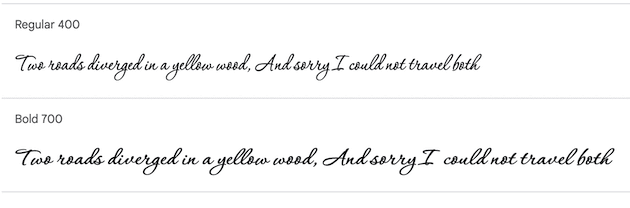
Corinthia อยู่ในหมวดสคริปต์และสื่อสารความรู้สึกสร้างสรรค์ มันคล้ายกับลายมือเขียนเล่นหางและอาจเหมาะสำหรับร้านบูติกหรือเว็บไซต์ของช่างฝีมือ ควรใช้แบบอักษรนี้สำหรับชื่อหน้าหรือส่วนหัว (และไม่ใช่สำหรับข้อความที่ยาวกว่า) เนื่องจากการวนซ้ำและเส้นโค้งอาจทำให้อ่านยากเล็กน้อย
4. อเลเกรยา
Alegreya เป็นแบบอักษรเซอริฟอีกแบบหนึ่งที่คุณสามารถใช้บนเว็บไซต์ของคุณได้ เดิมทีมันถูกสร้างขึ้นสำหรับวรรณกรรม ดังนั้นจึงเหมาะสำหรับข้อความยาวๆ นอกจากนี้ยังใช้งานได้ดีกับบล็อกวรรณกรรมหรือร้านหนังสือเสมือนจริง
5. เปิด Sans
Open Sans เป็นฟอนต์ sans serif พื้นฐาน สามารถใช้กับเว็บไซต์ระดับมืออาชีพด้วยการออกแบบที่เรียบง่าย นอกจากนี้ยังเหมาะสำหรับข้อความที่ยาวขึ้นเนื่องจากความชัดเจนและเป็นมิตรกับผู้ใช้
6. การแสดงเพลย์แฟร์
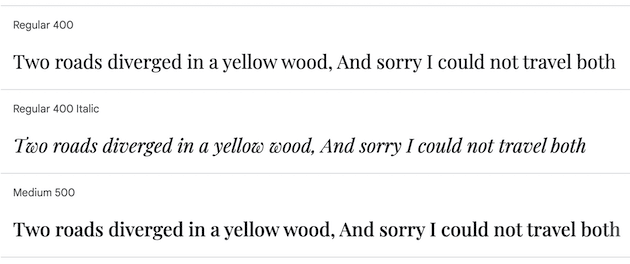
Playfair Display เป็นฟอนต์เซอริฟที่มักใช้ในนิตยสารแฟชั่นและเนื้อหาเกี่ยวกับบรรณาธิการเนื่องจากสไตล์ที่หรูหรา นอกจากนี้ยังอาจเป็นตัวเลือกที่ดีสำหรับพอร์ตการลงทุนระดับมืออาชีพ มีความหลากหลายและมีน้ำหนักให้เลือกมากมาย คุณจึงสามารถจับคู่กับฟอนต์เพื่อการตกแต่งได้มากขึ้น
7. ลาโต้
Lato เป็นแบบอักษรเปล่าที่ให้ความรู้สึกสะอาดตาและทันสมัย เป็นสมาชิกของตระกูล sans serif และเหมาะสำหรับเว็บไซต์ของบริษัทหรือธุรกิจที่ต้องการสร้างความน่าเชื่อถือ คุณสามารถจับคู่กับฟอนต์ที่มีชีวิตชีวาขึ้นเล็กน้อย ขึ้นอยู่กับบรรยากาศที่คุณต้องการ
8. โรโบโต้
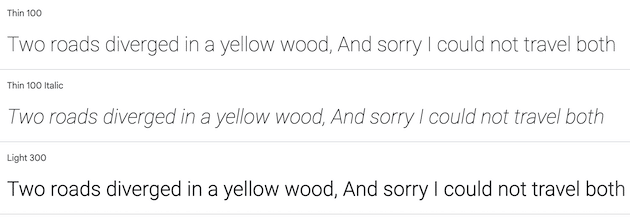
Roboto เป็นหนึ่งในแบบอักษรที่ได้รับความนิยมสูงสุดบนอินเทอร์เน็ต ใช้เป็นแบบอักษรเริ่มต้นสำหรับ Chrome OS ซึ่งเป็นตัวเลือกที่อ่านได้และเข้าถึงได้ ดังนั้นจึงเป็นฟอนต์ที่ดีสำหรับเว็บไซต์และธุรกิจที่ต้องการสื่อสารถึงความน่าเชื่อถือและความคุ้นเคย
วิธีเลือกฟอนต์ที่เหมาะกับเว็บไซต์ของคุณ
ตอนนี้เราได้ดูคำแนะนำบางส่วนแล้ว มาดูวิธีเลือกแบบอักษรที่เหมาะสมสำหรับเว็บไซต์ของคุณกัน ต่อไปนี้คือสิ่งที่ควรพิจารณาก่อนตัดสินใจ
ขั้นตอนที่ 1: คิดถึงเสียงของแบรนด์และค่านิยมของคุณ
เมื่อตัดสินใจว่าจะเลือกแบบอักษรใด สิ่งสำคัญคือต้องคำนึงถึงคุณลักษณะของตัวเลือกต่างๆ ของคุณและดูว่าสอดคล้องกับเสียงและค่านิยมของแบรนด์ของคุณหรือไม่ เป็นการดีที่คุณจะต้องบอกเล่าเรื่องราวของคุณผ่านตัวเลือกแบบอักษรของคุณ
ตัวอย่างเช่น Wild at Heart เป็นร้านดอกไม้ออนไลน์ที่มีแบบอักษรที่สะท้อนถึงคุณค่าของแบรนด์:
ตัวอย่างเช่น คุณต้องการให้เว็บไซต์ของคุณถ่ายทอดความเป็นมืออาชีพหรือความสนุกสนาน ลองคิดรายการคำคุณศัพท์และมองหาแบบอักษรที่สื่อถึงลักษณะที่คุณต้องการ
ขั้นตอนที่ 2: ทดสอบแบบอักษรบนอุปกรณ์ต่างๆ
เมื่อคุณจำกัดตัวเลือกของคุณให้แคบลงแล้ว คุณสามารถลองดูแบบอักษรแต่ละแบบบนอุปกรณ์ต่างๆ ได้ ด้วยวิธีนี้ คุณจะมั่นใจได้ว่าสามารถอ่านและตอบสนองได้ ความสามารถในการอ่านเป็นสิ่งสำคัญสำหรับทั้งผู้เยี่ยมชมและการปรับแต่งเว็บไซต์ให้ติดอันดับบนเครื่องมือการค้นหา (SEO)
เพียงเพราะเพจของคุณดูน่าทึ่งบนแล็ปท็อป ไม่ได้หมายความว่าจะแสดงผลได้ดีบนอุปกรณ์พกพา หากแบบอักษรดูผิดปกติในการแสดงตัวอย่างใดๆ คุณอาจต้องการกำจัดตัวเลือกนั้นและไปยังแบบอักษรถัดไป
ขั้นตอนที่ 3: จัดอันดับแต่ละแบบอักษรตามความสำคัญ
ตามหลักเกณฑ์ทั่วไป คุณจะต้องใช้แบบอักษรไม่เกินสามแบบในไซต์ของคุณ เกินกว่านั้นจะจำกัดการเข้าถึงและทำให้ไซต์ของคุณดูยุ่งเหยิง
เมื่อคุณเลือกสามตัวเลือกแรกของคุณแล้ว คุณสามารถตัดสินใจได้ว่าจะใช้แบบอักษรใดเป็นแบบอักษรหลักของคุณ ซึ่งจะอยู่ที่ด้านหน้าและตรงกลางของเว็บไซต์ของคุณ เช่น แบนเนอร์หรือส่วนหัวของคุณ รองของคุณจะทำหน้าที่เป็นกลุ่มของเนื้อหาที่เป็นลายลักษณ์อักษรของคุณ:
คุณสามารถใช้ตัวเลือกที่สามสำหรับคำกระตุ้นการตัดสินใจ (CTA) และโลโก้ อย่าลังเลที่จะปรับแต่งฟอนต์ต่างๆ เพื่อดูว่าฟอนต์ใดเข้ากันได้ดีที่สุดก่อนตัดสินใจขั้นสุดท้าย
บทสรุป
แบบอักษรสามารถช่วยคุณบอกเล่าเรื่องราวของแบรนด์ของคุณได้ การเลือกแบบอักษรที่เหมาะสมจะช่วยให้ผู้เข้าชมเข้าใจข้อความและค่านิยมของคุณได้ดีขึ้น นอกจากนี้ยังช่วยให้คุณสร้างการจดจำแบรนด์ได้อีกด้วย
หากคุณต้องการสื่อสารความน่าเชื่อถือและความเป็นมืออาชีพ คุณสามารถใช้ฟอนต์ serif เช่น Playfair Display และ Merriweather หรือคุณอาจต้องการเล่นหางสนุกๆ เช่น Corinthia ในขณะเดียวกัน แบบอักษร sans serif ที่สะอาดเช่น Open Sans สามารถทำให้เนื้อหาของคุณอ่านง่ายขึ้น